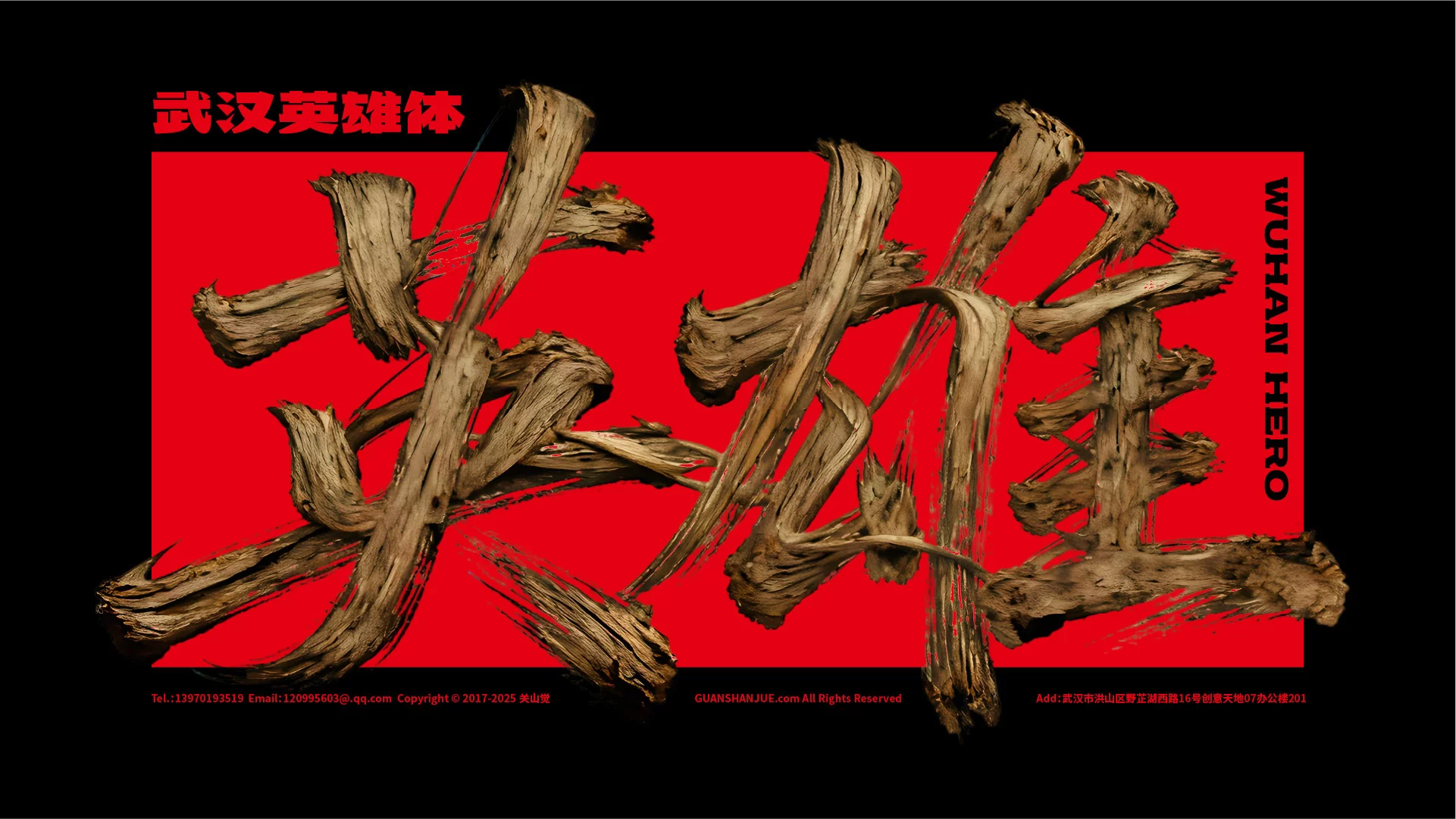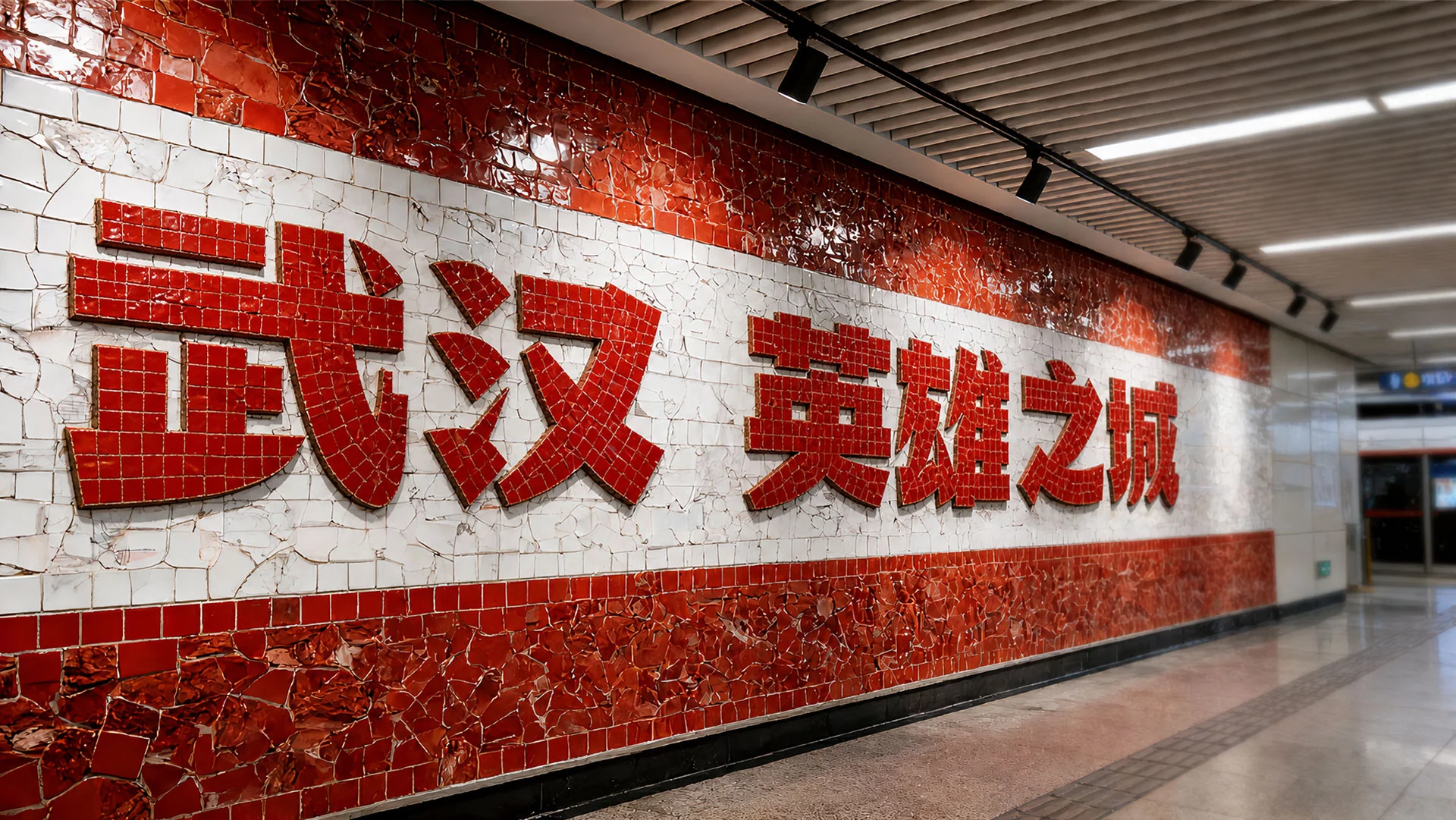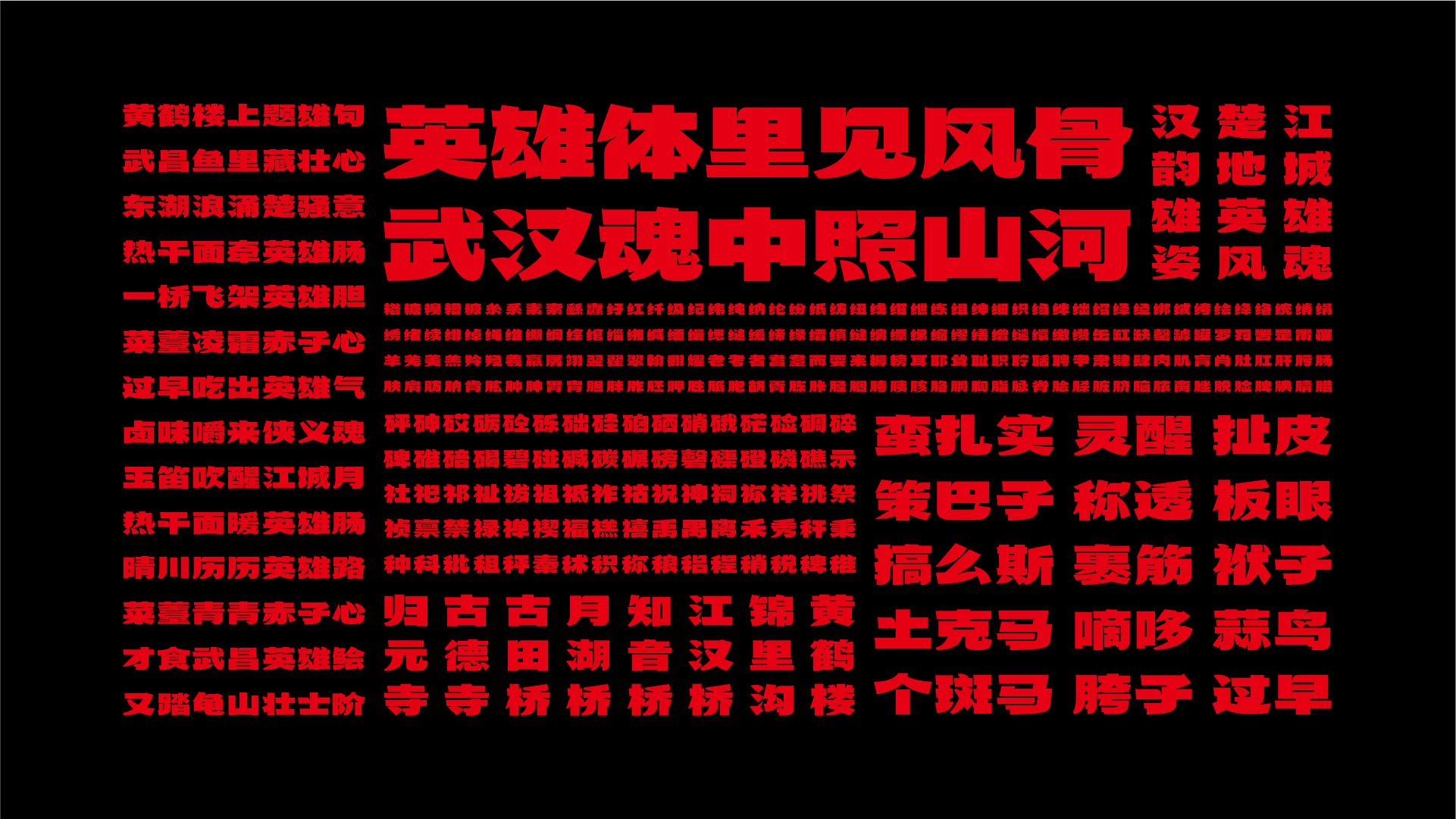
武汉英雄体由徐郑冰教授团队耗时两年手工打造,收录 6700 余汉字,笔画融合黄鹤楼、长江大桥等武汉城市元素,字形浑厚大气,自带荆楚英雄风骨。字体适合海报、短视频标题、文旅文创、宣传物料使用,本文提供正规下载方式,附带字体特性、使用场景与版权注意事项,设计师可放心取用。
武汉英雄体是极具城市辨识度的原创美术字体,由字绘中国团队手工创作,将黄鹤楼飞檐、长江大桥等江城元素融入笔画结构,字形宽扁稳重、力量感十足。整套字库字符齐全,广泛适配海报、短视频封面、文旅宣传、文创设计。
字体整体字形偏宽扁,笔画扎实厚重,结构稳健,视觉冲击力很强。
字体名称中的 “英雄”,承载着武汉的城市精神,字体气质坚毅大气,无论是国风作品、城市公益宣传,还是文旅相关设计,都能够快速烘托画面氛围。
相比常规黑体、宋体,武汉英雄体拥有独一无二的辨识度,用作主标题可以立刻拉开画面层次感,打造富有荆楚文化气息的视觉效果。